1、田英章,l950年生于天津,字存青、存卿,书法研究生,国家人事部干部。先后毕业于首都师范大学、日本东京学艺大学。 田英章系书法世家,自幼3岁时和其兄田蕴章习练书法,主功欧楷,兼学二王及历代名家碑帖。是屈指可数的楷书名家。硬笔楷书偏与秀丽飘逸,虽说他楷书学欧,毛笔在当今也是屈指可数,硬笔笔法感更贴近与《灵飞经》。现在市场上的字帖太多了,字库编排,要知道字库在制作过程中,经过软件调整秀气,难有手写之美,也造成了很多人认为他的硬笔楷书太过于“魅化,抗肩过重”等特点。也难免会对他的硬笔产生了一种审美疲倦之感,但是他的手写体个人觉得依旧很美,灵飞经的特点表现的淋漓尽致,所以也不要让字库误导了田师在硬笔上的成就。之前也有分享过他的老字贴,90年出版的,喜欢的可以点击“硬笔书法技巧”查看历史消息。
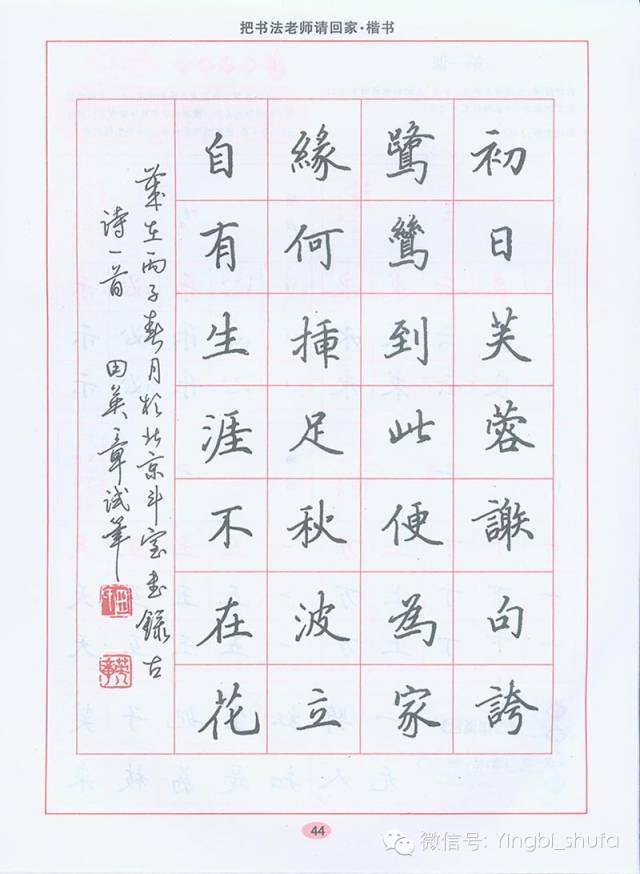
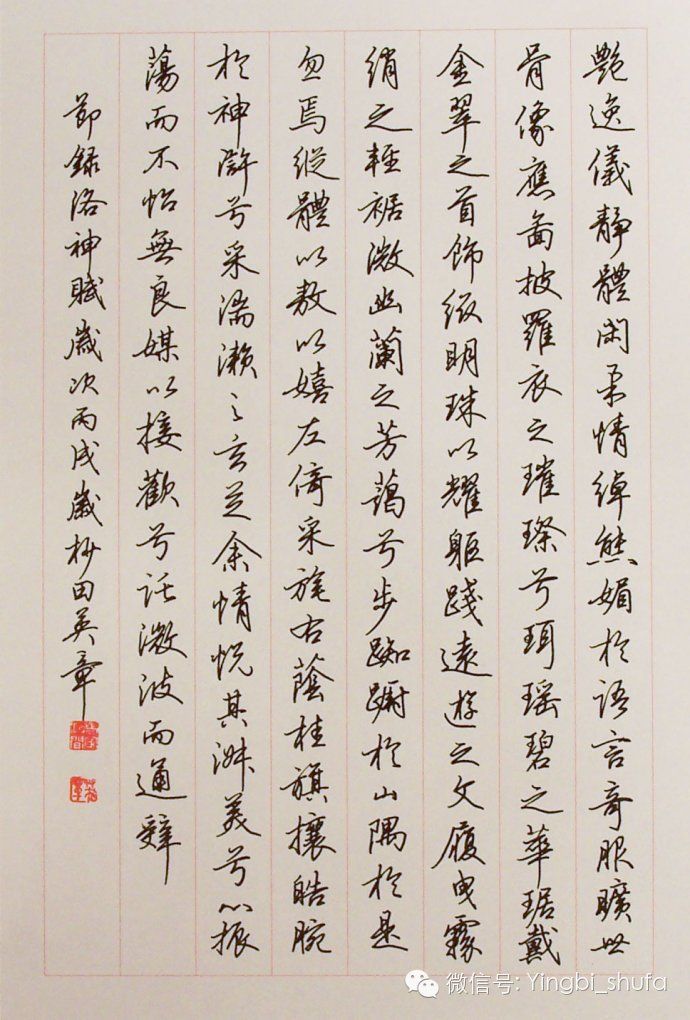
2、
卢中南,1950年12月出生。祖籍河南济源。现为中国人民革命军事博物馆设计处处长、研究馆员。第十届全国政协委员。中国书法家协会理事,中国博物馆学会会员。曾任中国书法家协会硬笔书法委员会副主任,中国钢笔书法大赛评委。
学欧体,擅长楷书,笔法秀美不失丰盈,结体端正,不扬不俗,柔中带刚。主页君手中也有卢中南老师的《欧阳询楷书全集临本》,不胜美哉。
金书《兰亭序》为中国美术馆收藏
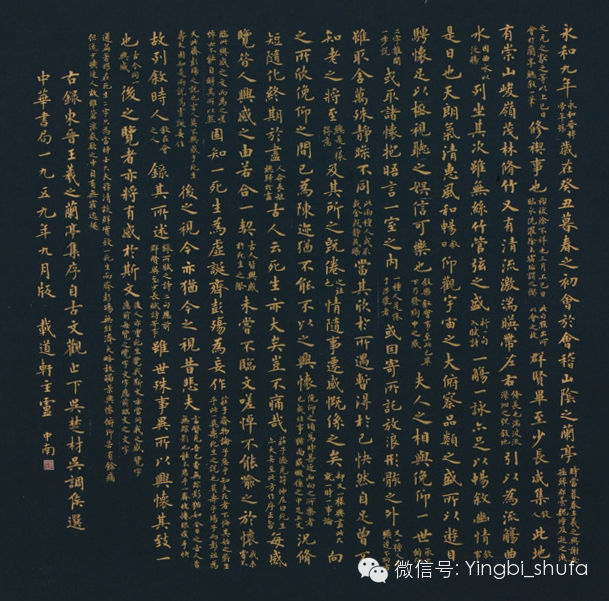
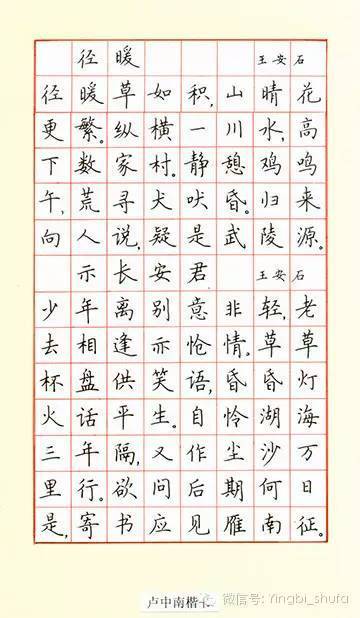
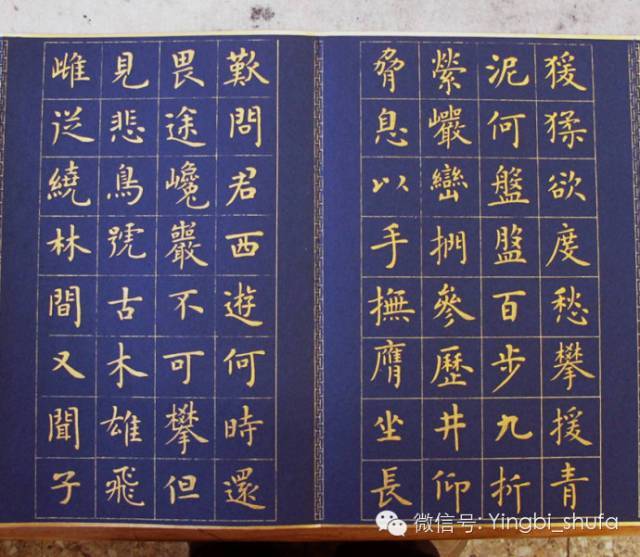
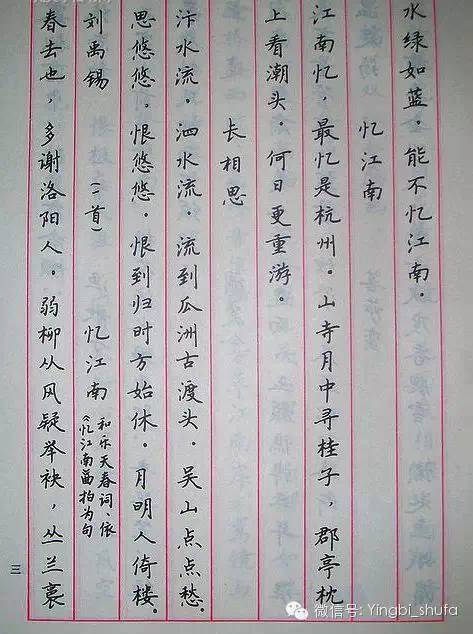
3 、吴玉生,1959年生,江苏人。多年临池不辍。担任过中国硬笔书法研究会副秘书长、华艺硬笔习字会副会长、中国书协函授培训中心副教授、中央电视台硬笔书法讲座主讲人和全国、全军书法赛事评委、编写出版书法教材字帖数十种。被北京市教育局评为“优秀书法辅导教师”,被中国教育学会书法教育研究会遴选为全国九年制义务教育《写字》课本规范字书写人。国家行楷手写体规范字形样本字书写人。
吴玉生是软笔、硬笔都颇有建树的书家,多年的教学实践,吴玉生总结了许多行之有效的教学和练字方法。
硬笔特点:温润秀劲,中宫紧凑且形态生动。特点非常易与掌握。
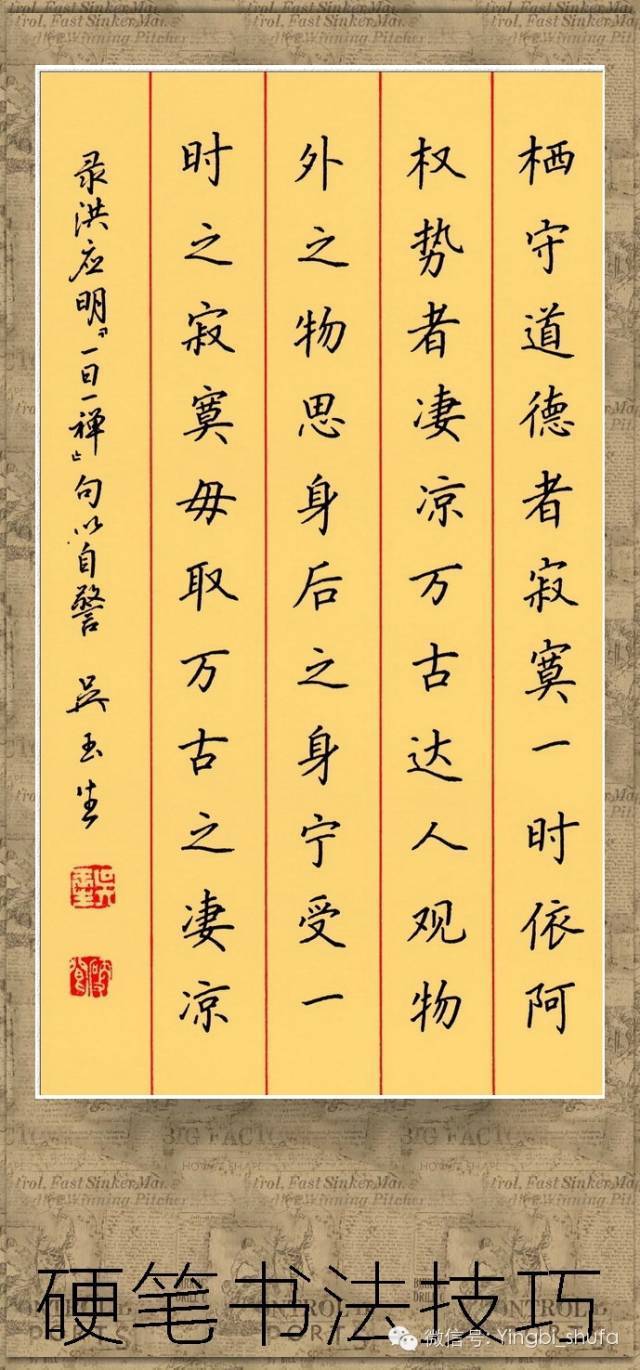
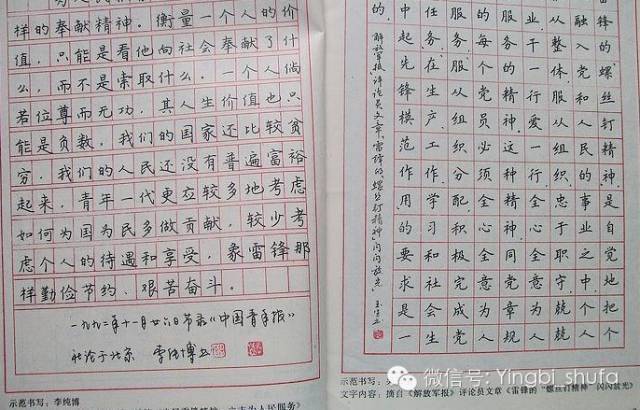
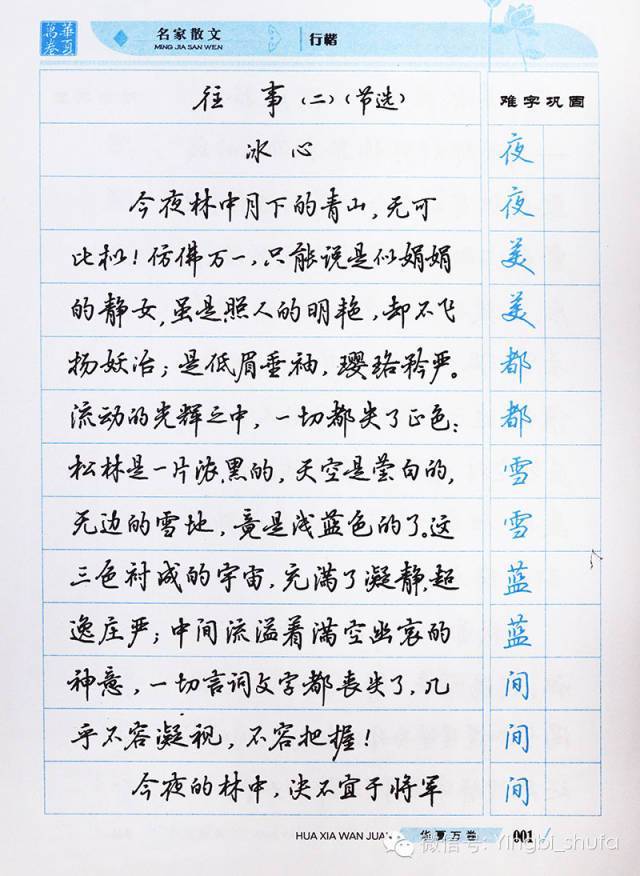
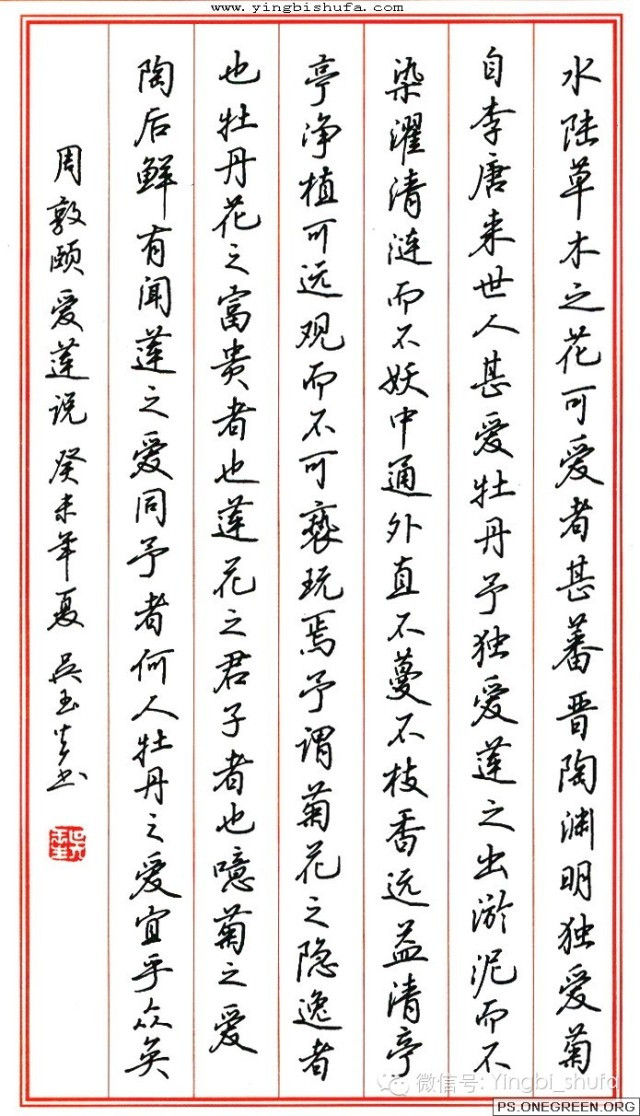
4、荆霄鹏
田英章弟子,中国硬笔书法协会会员、山西省书法家协会会员、山西省青年书法家协会理事、北京砚田书院特聘教授、《语文报·书法版》特约编委、特约高级书写员、《书法报·硬笔书法》特约创作员、大众书画院学术委员、关公书画院院士、傅山书画院院士。荆霄鹏,字昊之,田英章先生入室弟子,清华大学美术学院特聘书法教师,九年义务教育《写字》《书法》教材范字书写者。
虽说他是田师弟子,但是也有他自己独特的地方,笔法偏与温润,公整自然规范,这几年在各大书店,想必荆老师的字帖品种也是屈指可数了。想学习硬笔田楷的朋友,如果觉得田师的笔法掌握不好,大可以试试荆霄鹏的字。
5、顾仲安先生生于1956年,现任中国硬笔书法家协会副主席,中国硬笔书法家协会资格审查委员会副主任。 顾仲安连续四次荣获全国硬笔书法大赛最高奖。书法特点:从初唐楷法入手,又以此为基础,通过智永、陆柬之而上溯二王,遍临苏、黄、米、蔡及赵孟頫的书迹。最难能可贵的是,他把毛笔书法的神韵,巧妙地移植到钢笔字中来;细看他的字迹,在王字系统里可以窥见历代名家的痕迹,既具传统功底又有时代气息,字体结构严谨,点画精熟,还有毛笔书法的韵味。其楷书庄重典雅,娴静大方;行书酣畅潇洒,则劲隽秀;草书飘逸轩昂,雄健自然。笔势开拓,字形清劲秀丽,行笔抑扬顿挫,使这本字帖有一种奋进向上的气度,适合当今初学钢笔行书的广大读者临写。很多女生喜欢柔美秀丽的字,不妨选择顾仲安。
6、女中豪杰张秀:女,1962年7月生于武汉,湖北省博物馆研究员,中国书法家协会会员,湖北省书法家协会副主席,中国硬笔书法家协会理事,湖北省妇女书协副主席。张秀幼时始学颜书,书法特点存隶书笔意,刚劲明快,笔锋内敛简明,看其硬笔作品流露着一种古韵的风格。可惜的是,现在市面卖的字帖少之又少,很难一见新作品,老字帖也是有的,不过这样更能保留原貌风格,少了字库的匠气。